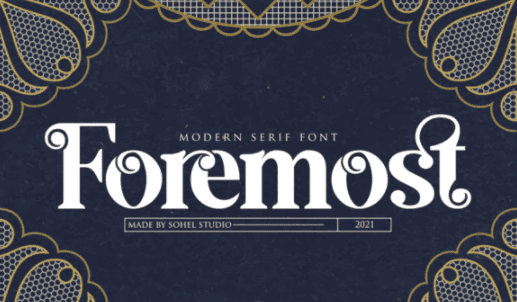
Название: Foremost Font (2021)
Foremost - стильный шрифт с засечками, который невероятно красиво смотрится как в крупном, так и в мелком начертании. Лучше всего он смотрится в заголовках и логотипах. Чистые линии и плавные изгибы Foremost придают любому проекту дополнительный штрих класса.
Этот шрифт идеально подходит для элегантного и роскошного логотипа, дизайна названия книги или фильма, модного бренда, журнала, одежды, надписей, цитат и многого другого.
Foremost - стильный шрифт с засечками, который невероятно красиво смотрится как в крупном, так и в мелком начертании. Лучше всего он смотрится в заголовках и логотипах. Чистые линии и плавные изгибы Foremost придают любому проекту дополнительный штрих класса.
Этот шрифт идеально подходит для элегантного и роскошного логотипа, дизайна названия книги или фильма, модного бренда, журнала, одежды, надписей, цитат и многого другого.